Mac Fan
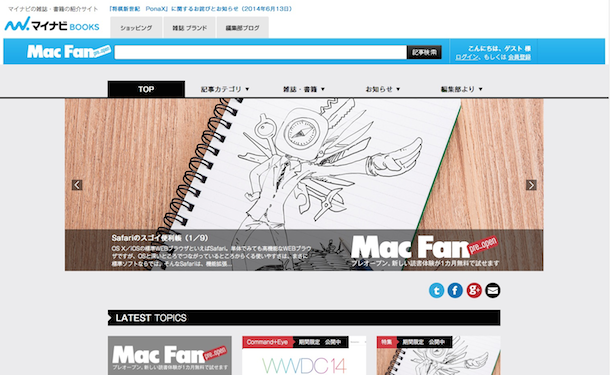
■どのようなサイトですか?
株式会社マイナビが発行する「Mac Fan」の公式サイトです。「使い方」より「使われ方」の視点で、Mac、iPhone、iPadといったアップル製品とアップル・カルチャーを中心に情報を編むInfortainment Mediaとして、さまざまな読書スタイルに応え、雑誌/WEB/アプリで記事をお届けしています。
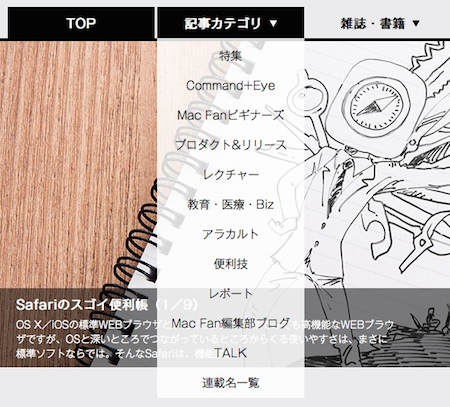
■TypeSquareを導入された背景を教えてください。
月刊の雑誌では4年前からモリサワのフォントを使用していました。公式WEBサイトはこれまで「雑誌の補完と読者サポート」を行う場でしたが、リニューアルにより「Mac Fanの記事をWEB上でも楽しんでいただく場」へ方向性を転換。内容に集中して記事を読み進めていただくために、これまで雑誌で使い続けてきたモリサワフォントをWEBでも使用したいと考えました。
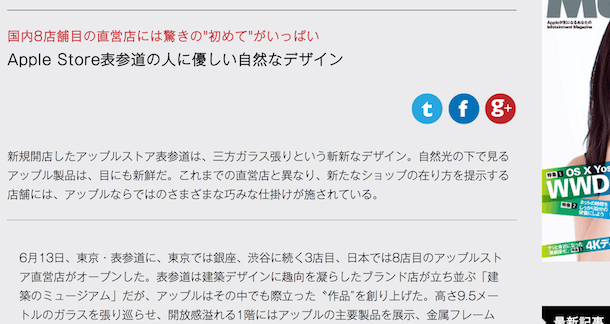
WEBサイトでメインに使っているのはゴシックMB101ファミリーです。誌面でもよく使っているフォントであり、どんな内容の記事でも、また長い文章であってもすっきりと読み進めてもらえるフォントだということで、このフォントを選びました。
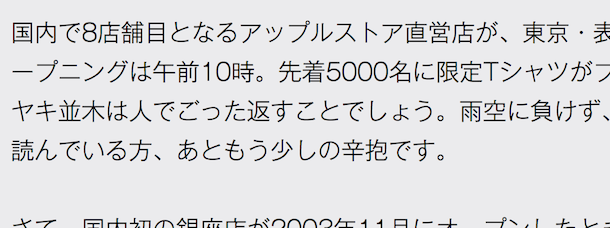
■ご利用の書体名
ゴシックMB101 L / R / M